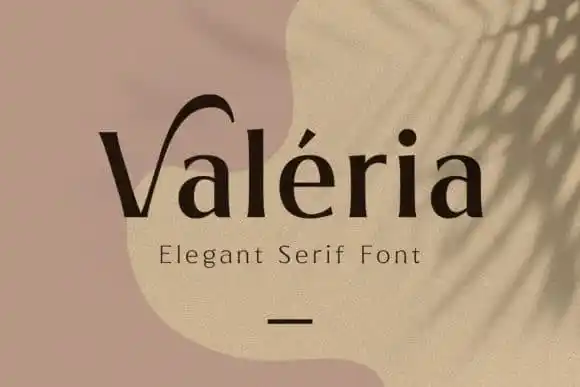
Valeria Sans Serif Font – Fonte Grátis
Valeria Sans Serif Font
A Valeria Sans Serif é uma fonte serifada moderna com grande contraste entre os traços, que cria um estilo minimalista elegante. Arterfak Project concebeu esta fonte sofisticada, criando uma aparência que combina a arquitetura clássica do século XX com o refinamento da era contemporânea. Além de seu contraste apreciável, a Valeria também oferece ligaturas bem-feitas e um vasto número de alternativas de forma especializadas para um uso ilimitado. A multilíngue é outro ponto forte desta fonte, que ajuda a expandir seus horizontes criativos ao longo do mundo. Se você busca dar um toque sofisticado a suas próximas criações, a Valeria Sans Serif certamente fará isso de forma luxuosa e elegante. Não hesite em experimentar este charme único.